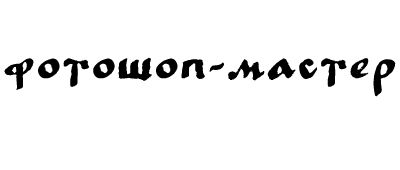
Шрифт - LC Bagira
Интересный шрифт, который хорошо подходит для работы в фотошопе. Есть поддержка русского языка.
Внешний вид:
как в советских мультиках:)